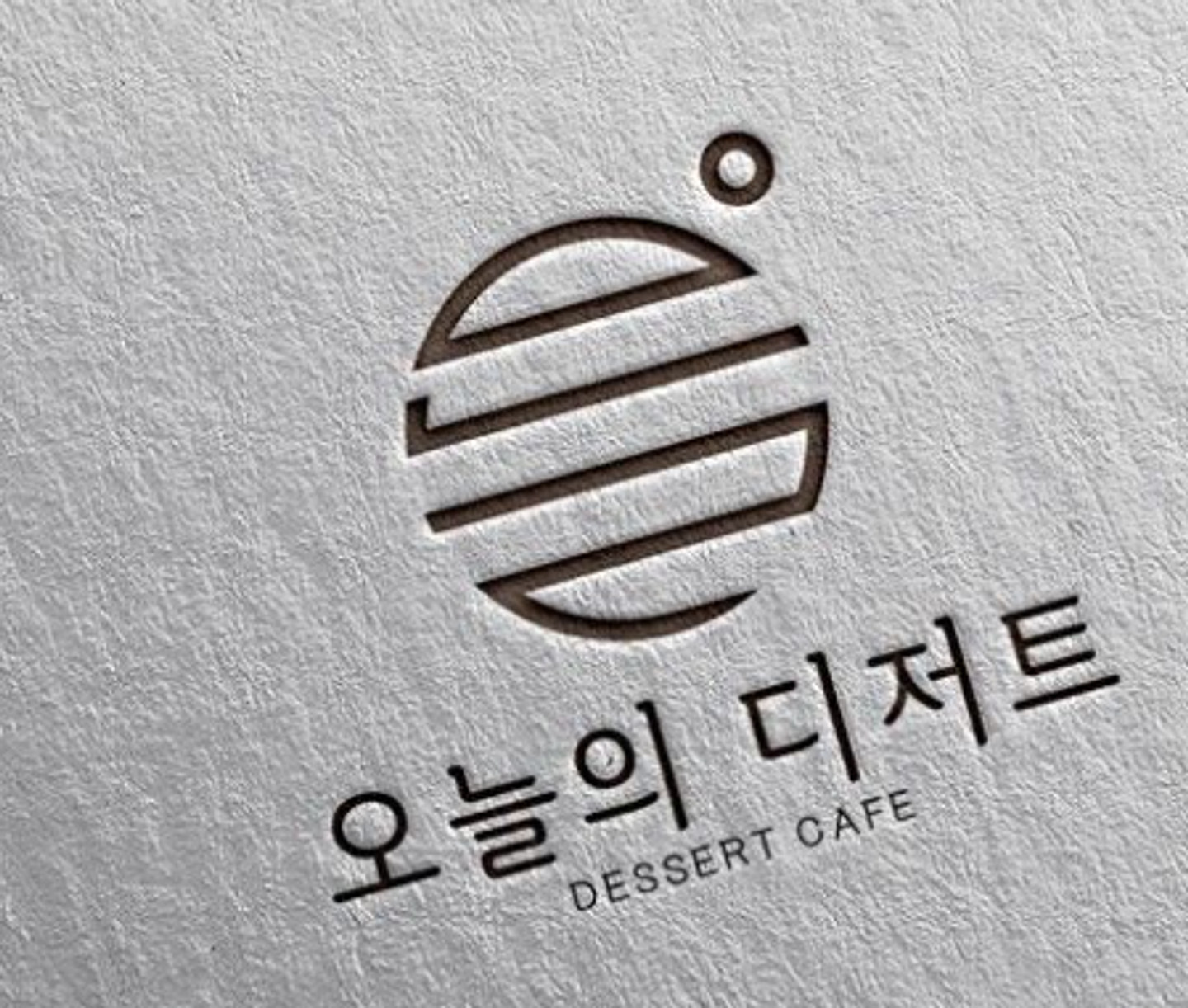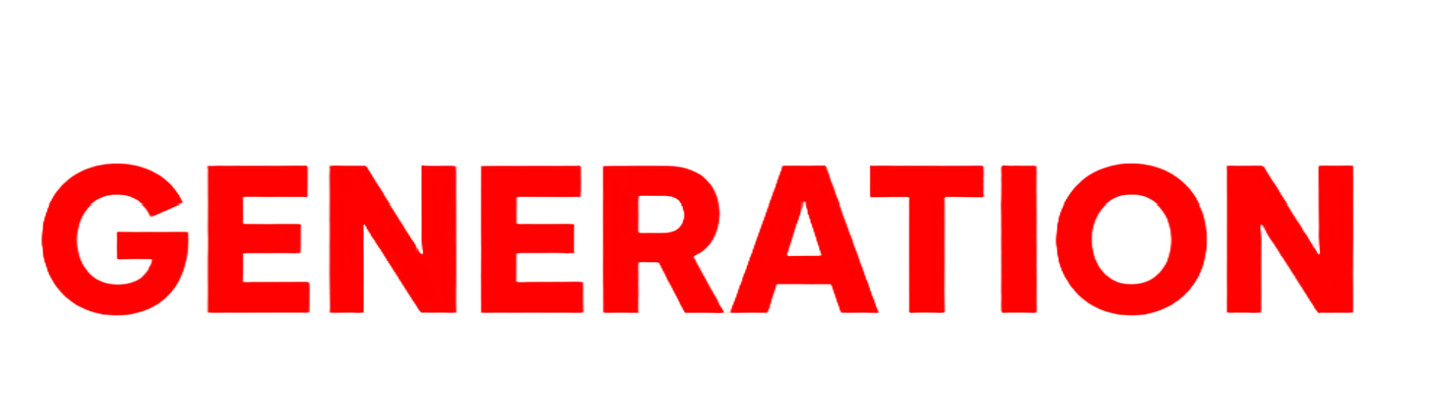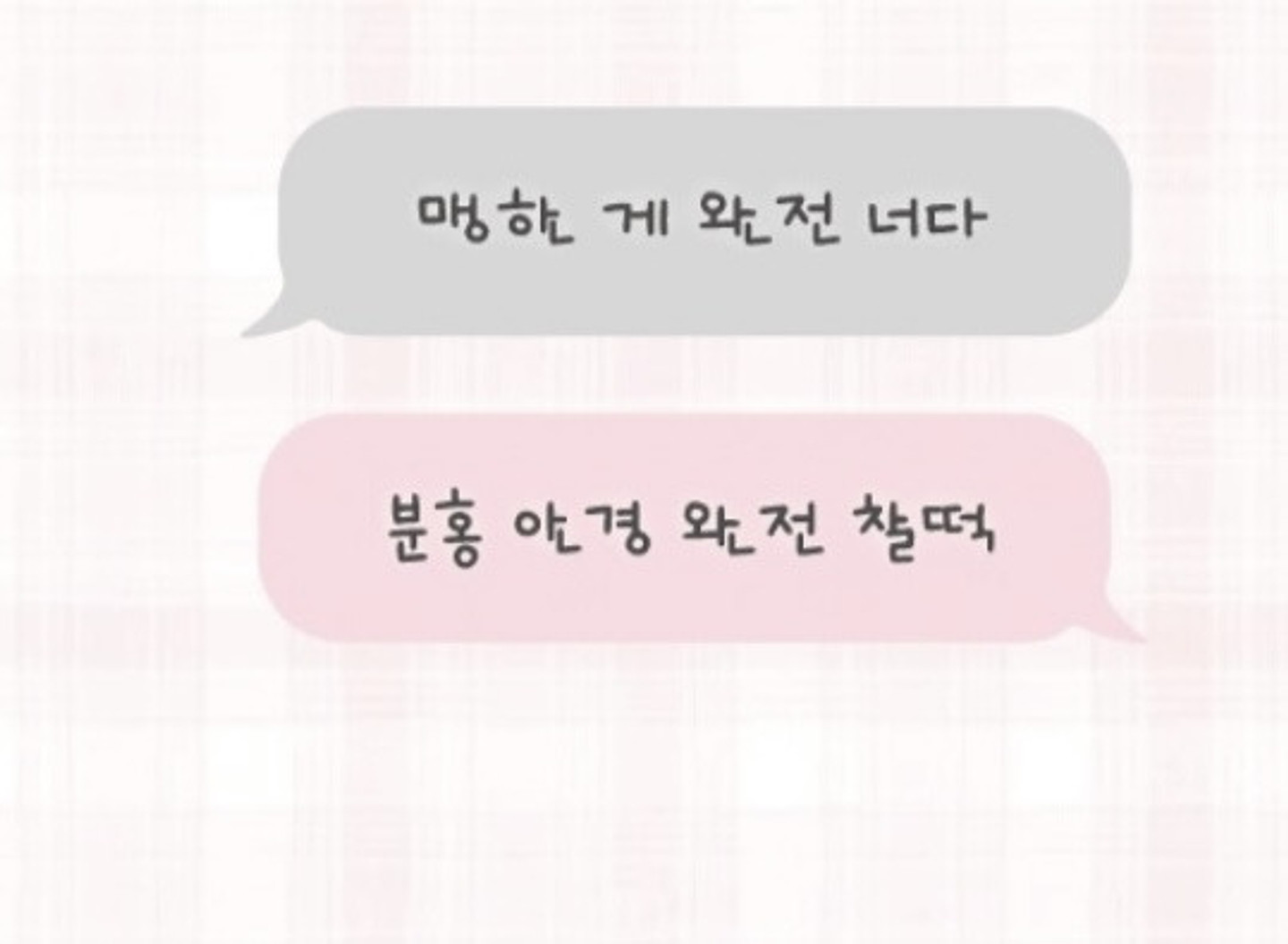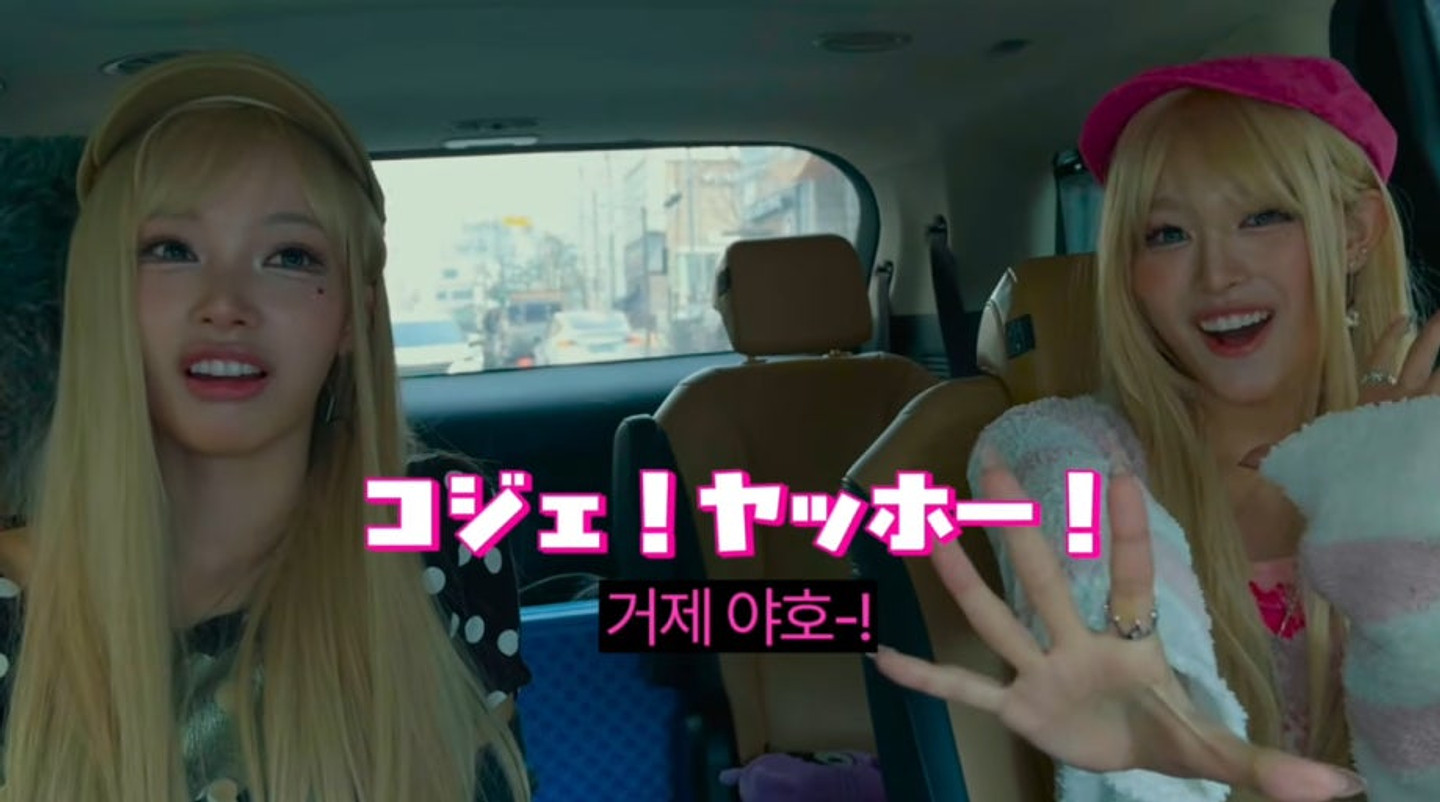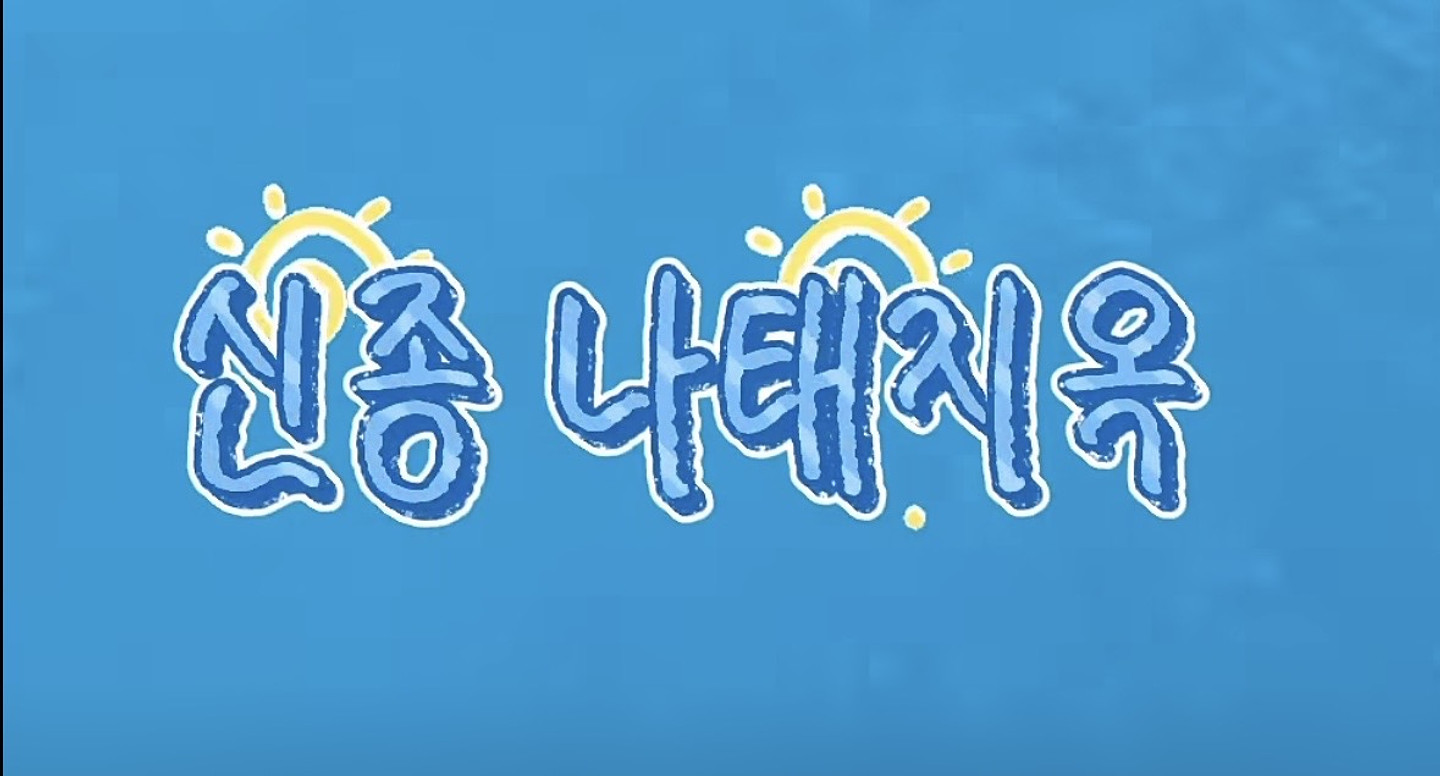
엔시티위시 요이돈 앨범 커버인데 무슨 폰트길래 이렇게 귀엽나요 ㅠㅠㅠㅠㅠㅠ
폰트 이름 궁금해요. 감사합니다~
인스타에서 봤는데 폰트가 뭘까요?
전에 작업하면서 봤던 폰트를 대략적인 기억으로 그려봤는데 이 형태와 가장 가까운 폰트가 있을까요? 제 기억이 맞다면 잠깐 일하던 곳에서 산돌 클라우드가 깔려있던 것 같습니다.
Sk 와이번스 시절 마킹 폰트가 궁금합니다. 만약 없다면 비슷한 폰트라도 알려주셨으면 감사할것같아여
혹시 어떤 폰트인지 아실까요?ㅠㅠㅠ